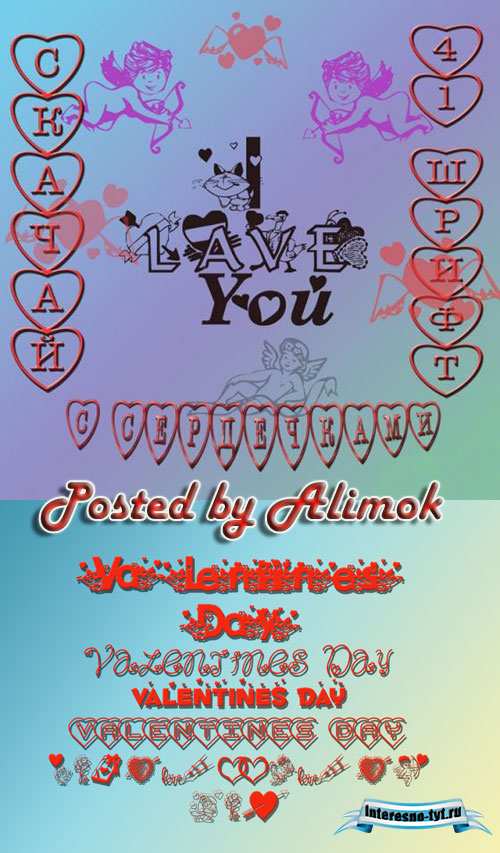
Набор шрифтов ко дню Святого Валентина
Красочный набор из 40 шрифтов с сердечками ко дню Святого Валентина. Идеальная подборка шрифтов для красивого оформления Ваших работ. Много символьных шрифтов.